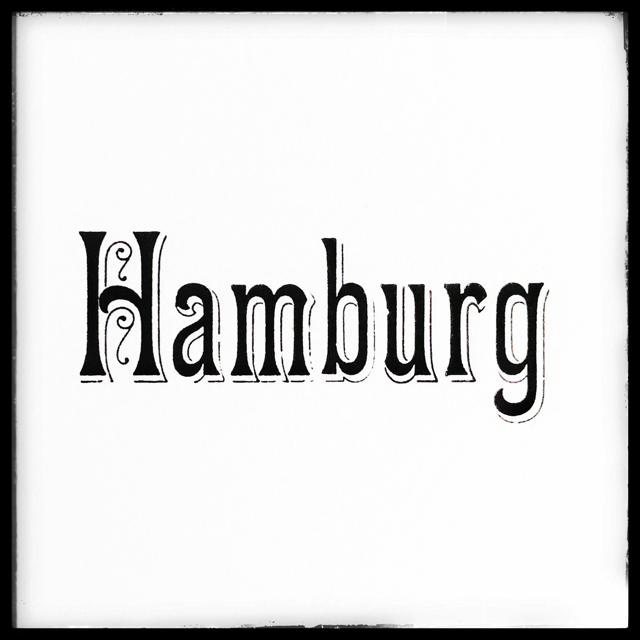
Unbekannte Bleisatzschrift
heute wende ich mich mal in Sachen Schriftidentifikation an euch.
Besagte Schönheit habe ich nicht im „Seemann“ finden können, auch andere Schriftmusterbücher gaben keine Auskunft.
Eventuell könnt ihr mir ja weiterhelfen. Besagte Schrift habe ich in 16, 24 und 36 Punkt.
Ich habe sie hier mal ganz vorsichtig angedruckt, ob ihres Alters sind die Lettern zum Teil doch schon strapaziert worden.
Die dürfte sich sicher in den Karten- oder Zirkularschriften einsortieren lassen. Das Thema hatten wie hier recht ausführlich durch genommen: